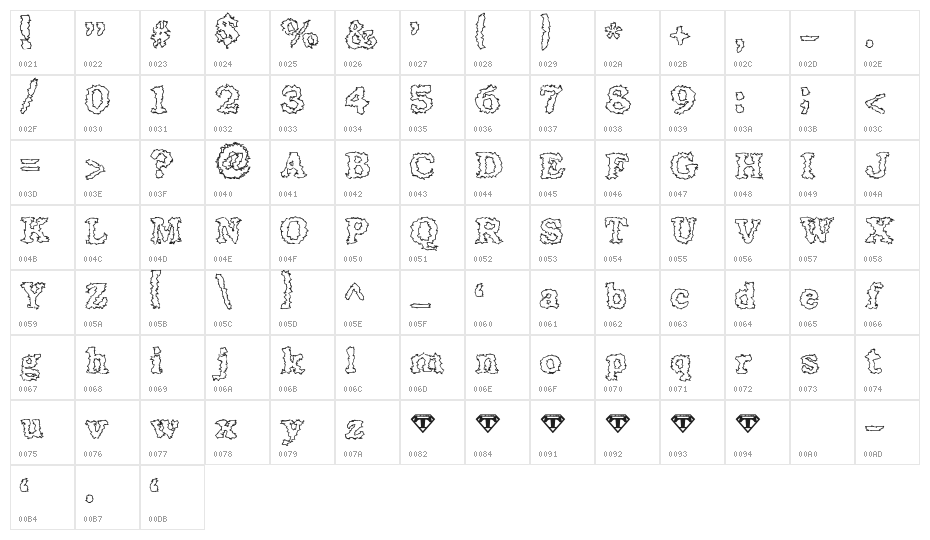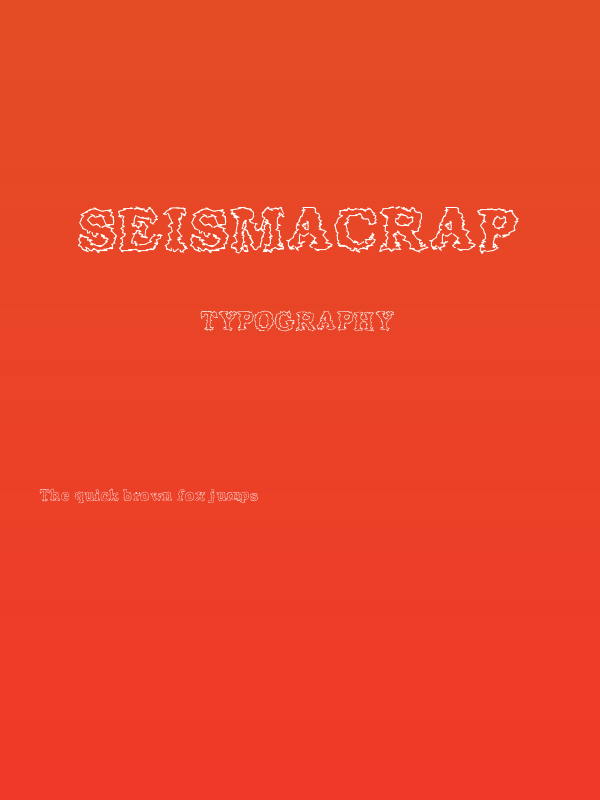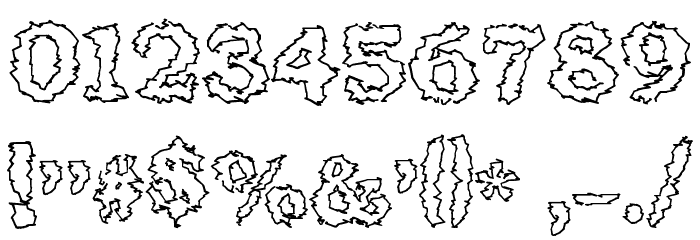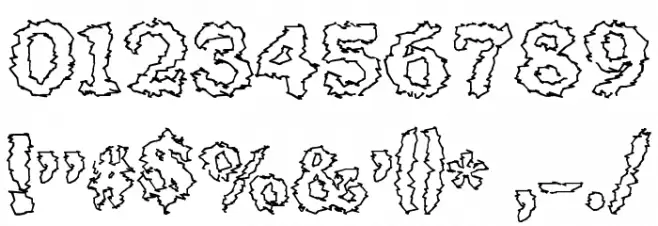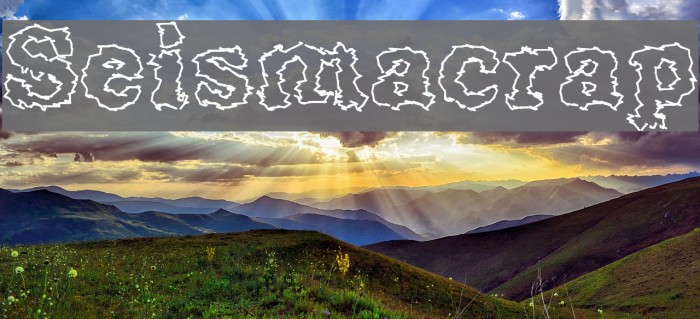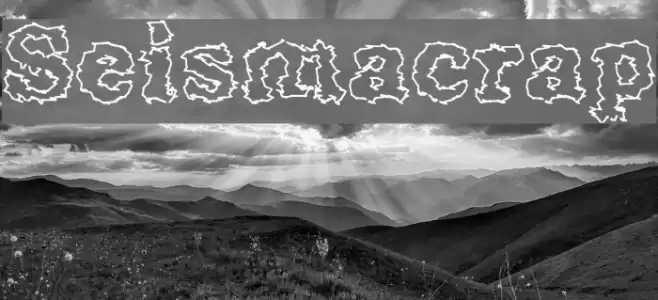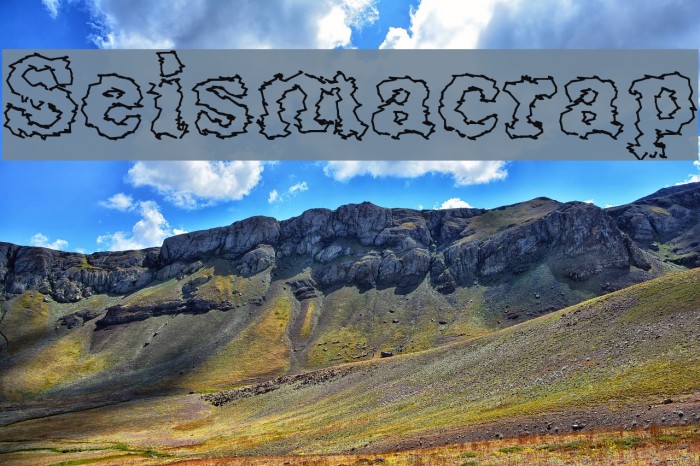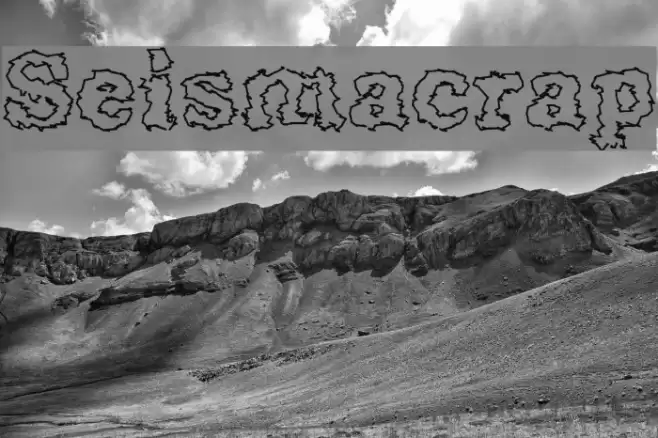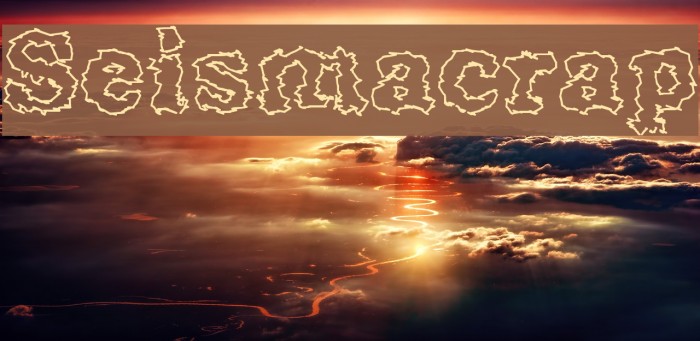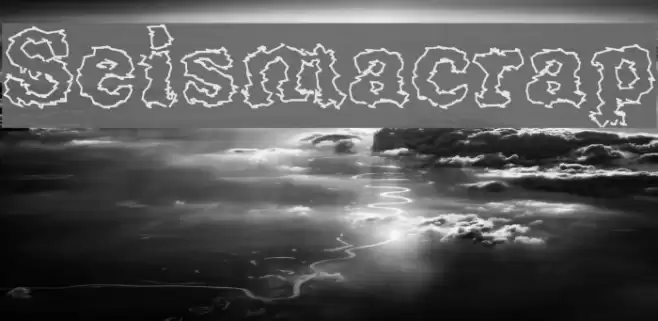
Seismacrap Font
Diese Schriftart enthält 103 Zeichen. Klicken Sie auf ein Zeichen für Details.
| Vorgeschlagene Projekte | Perfect for posters, album covers, adventure-themed branding, and any project needing a bold, dynamic look. |